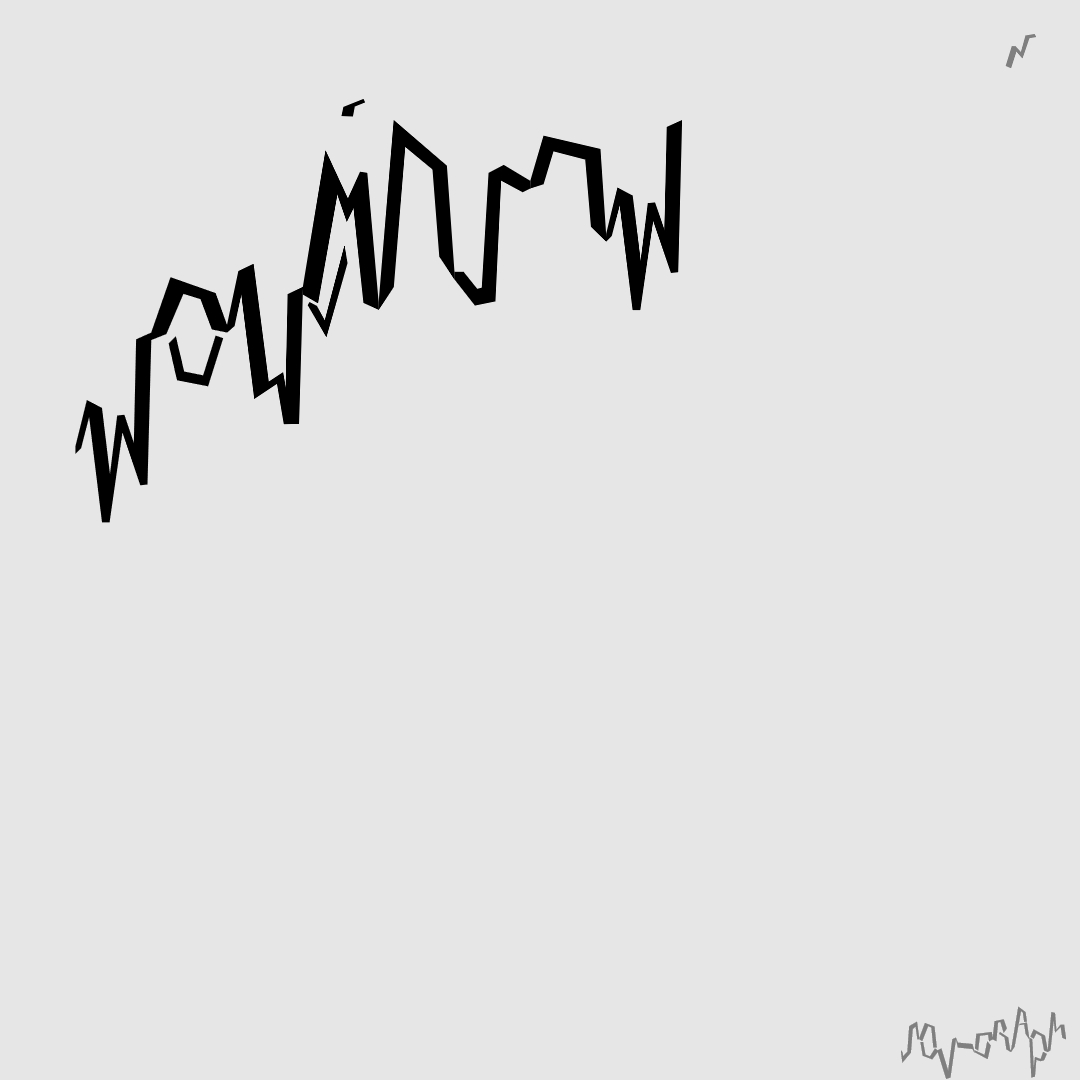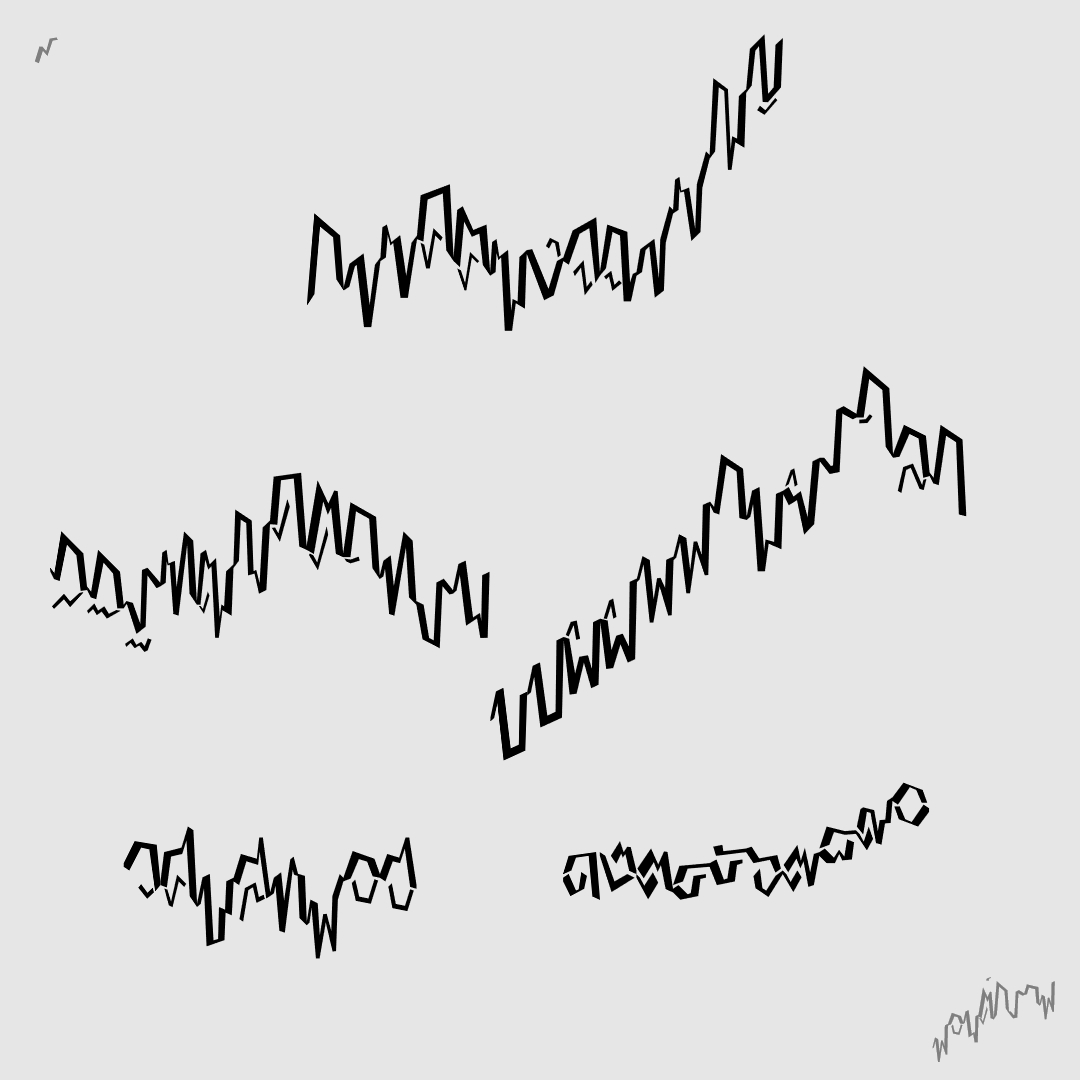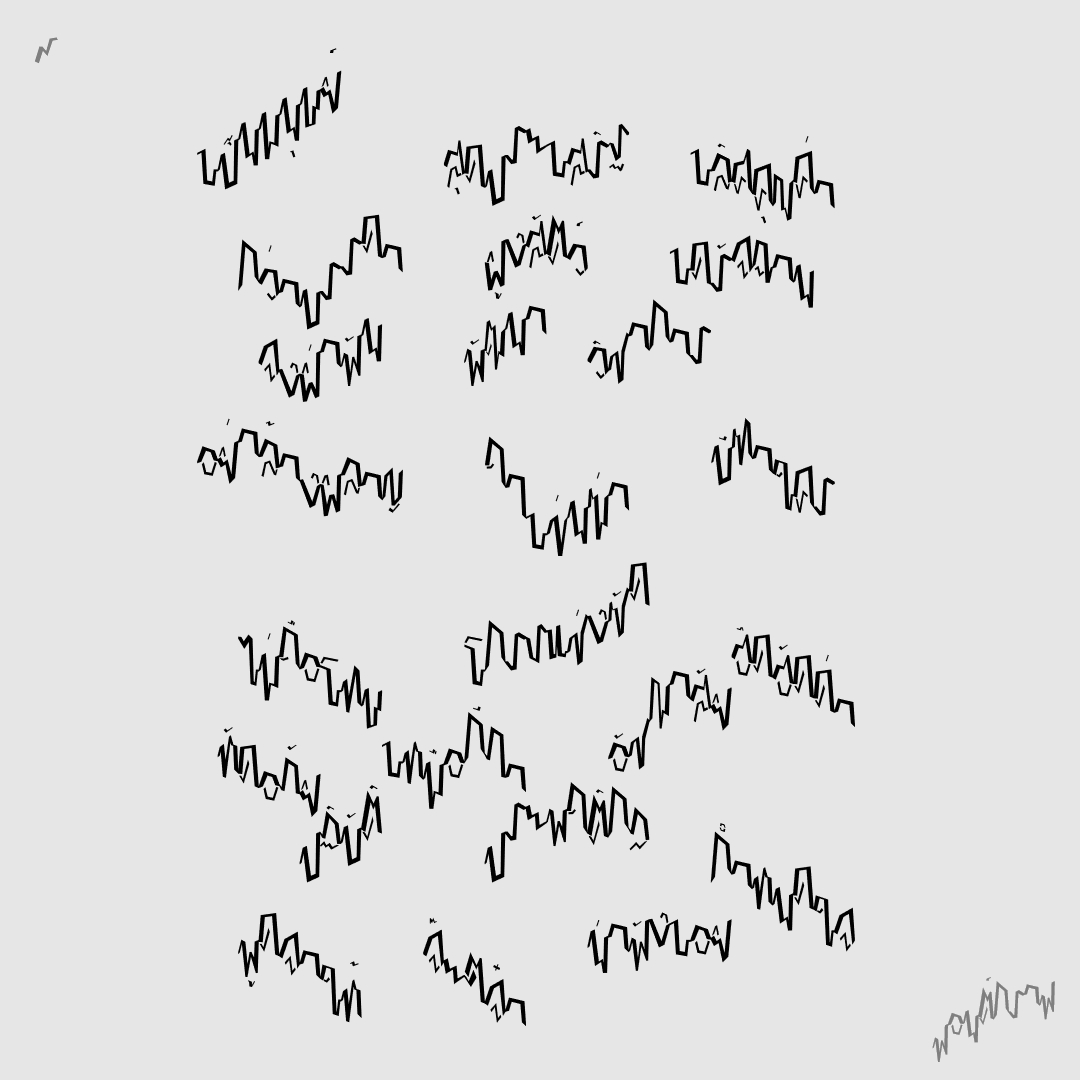
ฟอนต์ กราฟ
ฟอนต์แบบเส้นกราฟวิ่งขึ้นลง ไม่ถูกจำกัดอยู่ในบรรทัดเดียวแบบฟอนต์ปรกติ แต่นั่นก็สร้างปัญหา..จึงเป็นแค่พาดหัว
มี 2 แบบ ปรกติเส้นยาวต่อเนื่อง อ่านยากนิดนึง  กด bold แบบเส้นสั้นกว่า อ่านง่ายกว่านิดนึง แต่ความเป็นกราฟเส้นลดลง
ตัวอย่างอักษร
เหมาะกับประโยคเดียว
มี 2 แบบ
ไม่เหมาะบรรทัด หรืออะไรที่ต่อเนื่องยาวนาน
ปล. ฟอนต์นี้ติดค้างไว้หลายปี เพราะคิด solution ทำให้ฟอนต์ต่อกันไปเรื่อยๆไม่ได้นี่แหละ จนได้เทคนิคจากฟอนต์ชวเลขเกรกก์ไทย